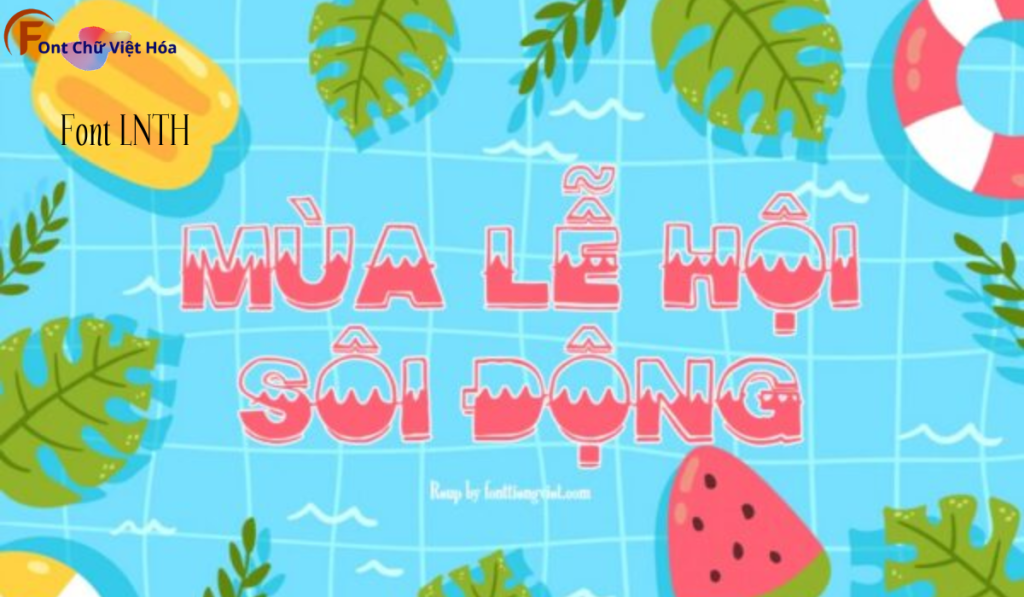
Font LNTH Midsummer Việt Hóa
Font LNTH Midsummer Việt Hóa là một font chữ nhẹ nhàng, thuộc bộ LNTH, với thiết kế thanh thoát và tinh tế. Phong cách của font này phù hợp với các dự án thiết kế cần sự nhẹ nhàng và tinh tế, như thiệp mời, bìa sách, hoặc logo. Font LNTH Midsummer Việt Hóa mang đến sự nhẹ nhàng và dễ nhận diện, ứng dụng trong các lĩnh vực sáng tạo. Đặc điểm hình dạng của font bao gồm các đường nét thanh mảnh và tinh tế, giúp tăng tính thẩm mỹ và sự chú ý. Việc Việt hóa font giúp người dùng dễ dàng sử dụng trong các thiết kế tiếng Việt, mang lại sự tiện lợi và linh hoạt.